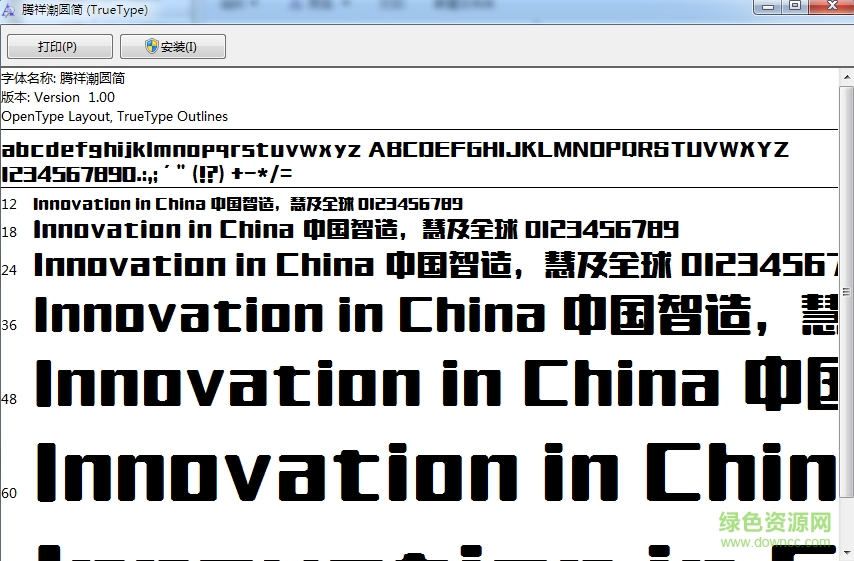
騰祥潮圓簡(jiǎn)
騰祥潮圓簡(jiǎn)是一款非常美觀的電腦字體,字形結(jié)構(gòu)扁方、端莊,橫豎筆畫粗細(xì)比例適度、豎筆粗壯有力,布白均勻、行文貫通,可用于印刷出版、包裝設(shè)計(jì)、廣告設(shè)計(jì)、網(wǎng)頁設(shè)計(jì)等領(lǐng)域,喜歡可以來綠色資源網(wǎng)下載!
字體簡(jiǎn)介
騰祥潮圓簡(jiǎn)是一款富于變化的美術(shù)類黑體,是在潮黑的基礎(chǔ)上變換設(shè)計(jì)而成。雖然字形結(jié)構(gòu)與潮黑相同,但兩款字的風(fēng)格氣質(zhì)截然不同。潮圓將潮黑的棱角柔化形成被融化之感,融化了的筆畫圓潤(rùn)富于親和力。